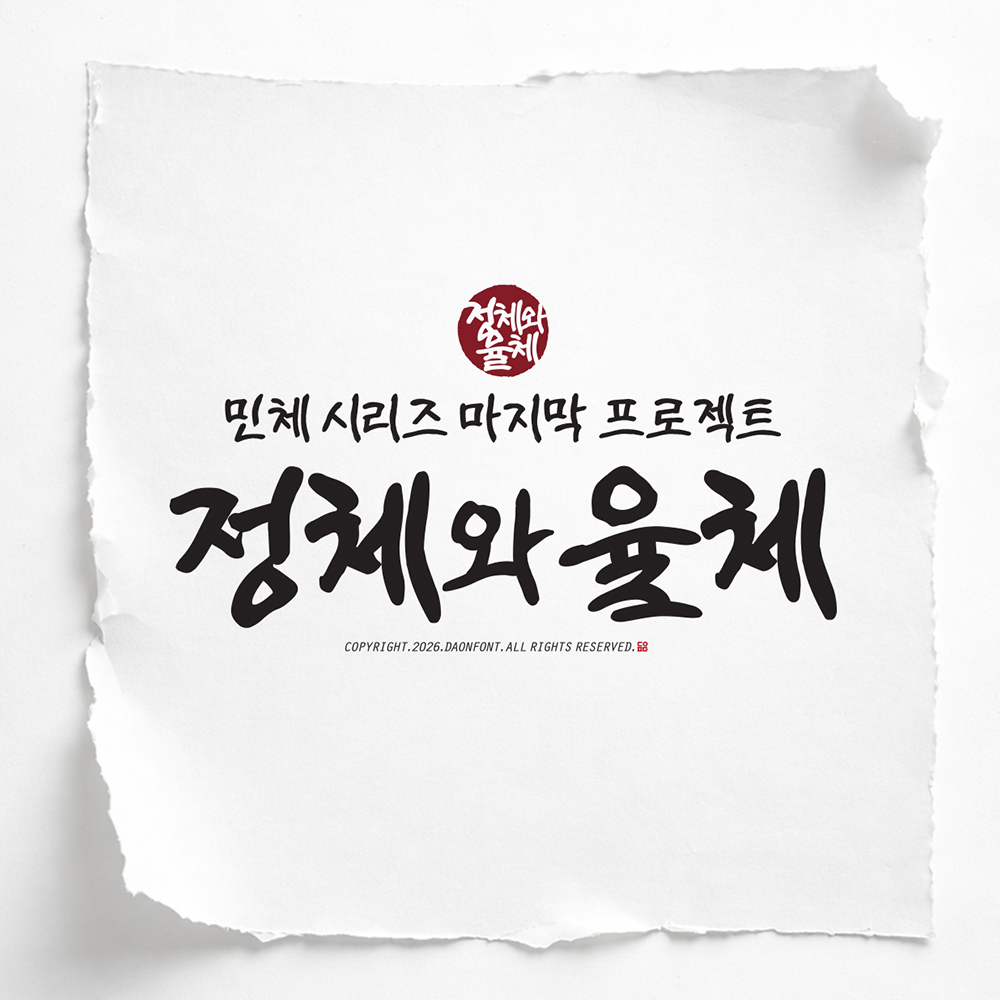
이번 프로젝트는 김성장 작가의 손글씨를 기반으로 제작된 서체로,
민체의 구조적 균형을 담은 어깨정체, 필획의 흐름과 리듬을 강조한 어깨율체 두 서체로 구성되어 있습니다.
어깨민체 시리즈를 잇는 서체 프로젝트로,
전통적인 민체의 분위기와 손글씨의 감성을 현대적인 폰트로 구현한 서체입니다.